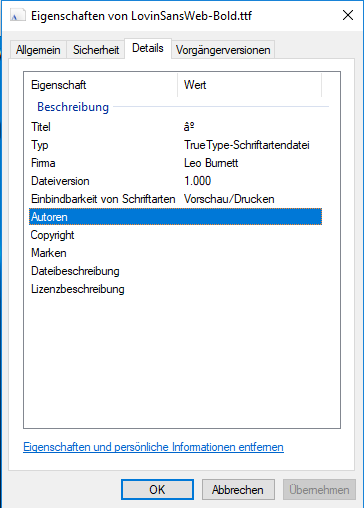
Woher stammt die Lovin’ Sans von McDonald’s?
Kennt jemand eine seriöse Quelle, die etwas zur Entstehung und dem Designer der Lovin’ Sans von McDonald’s verrät? Ich vermute, dass hier die Colfax zugrunde liegt, kann aber nirgends etwas stichhaltiges dazu finden. Eine Spur führt zu www.brianloehr.com wo das Alphabet der Schrift abgebildet wird, jedoch ohne Infotext geschweige denn vernünftigem Impressum.
Das steht in den Infos des Zeichensatzes. Die Version ist 1.0.  Die anderen Felder wie Designer, Copyright, Lizenz etc. sind leer. (Glyphs)
Wäre interessant zu wissen wer in Sachen Custom-Fonts noch beteiligt war. Laut den Arbeitsbeispielen scheint das bei Leo Burnett und Brian Loehr nicht zu ihrem Spezialgebiet zu gehören. In der Regel werden für solche Zwecke ja auch Schriftgestalter bzw. Foundries beauftragt.